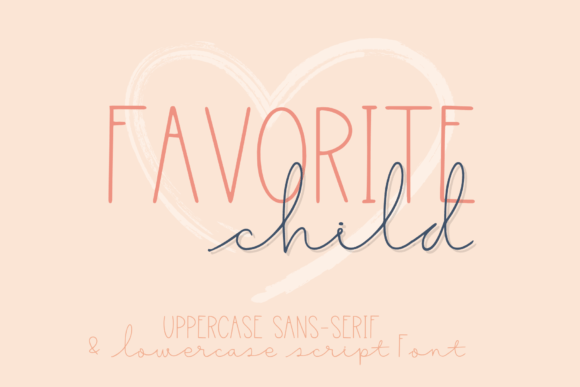
Favorite Child
**L'écriture parfaite pour les enfants de cœur : Favorite Child**
Une police d'écriture adorable et charmiante
Favorite Child est une police d'écriture charmante et adorable qui émet une aura de jeu et de bonheur. Avec ses courbes charmantes et ses traits fantaisistes, Favorite Child est parfaite pour ajouter une touche de personnalité et de douceur aux invitations, cartes de vœux, graphiques de réseaux sociaux et à tout projet qui nécessite une touche de jeu et de délice.
**Les avantages de Favorite Child**- UA codée PUA : accédez à tous les glyphes et les traits sans effort !
- Polissez vos créations avec des courbes et des traits charnières qui donnent une touche de personnalité à votre travail.
- Idéal pour les projets d'enfants : Favorite Child est la police d'écriture parfaite pour les invitations de baptême, les cartes de vœux et les créations pour enfants.
- Créer des invitations de baptême ou de mariage à la fois charmantes et originales
- Donner une touche de douceur à vos cartes de vœux ou de remerciement
- Créer des graphiques de réseaux sociaux qui reflètent votre personnalité